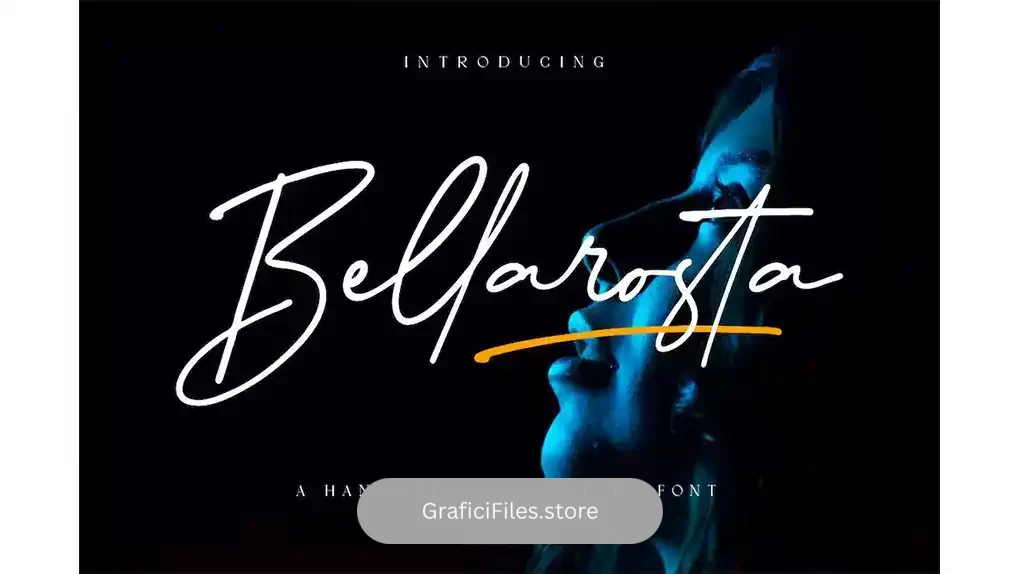
دانلود فونت انگلیسی به سبک امضا Bellarosta – Signature Font
فونت انگلیسی به سبک امضا : این مجموعه شامل یک فونت به سبک امضا است که برای لوگو، برندینگ، تبلیغات، مجلات، محصولات زیبایی، کارت ویزیت، عروسی، نقل قول و پوشش متنی بر روی تصویر پس زمینه مناسب میباشد.
• عنوان مجموعه: Bellarosta – Signature Font